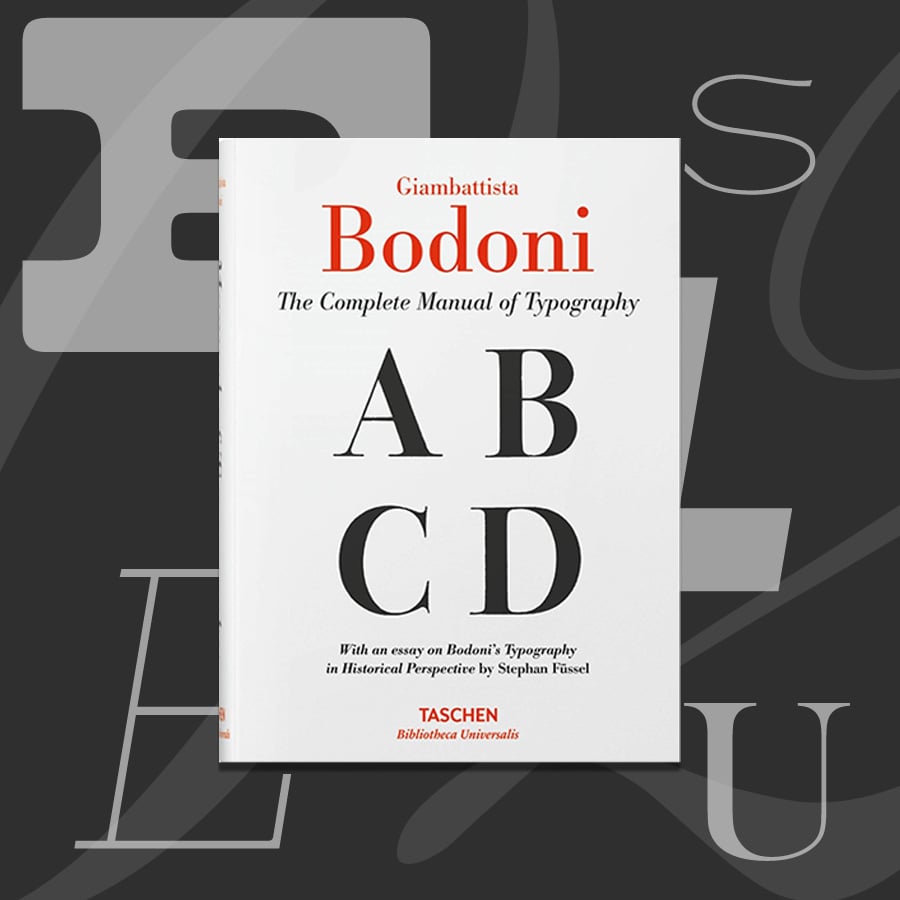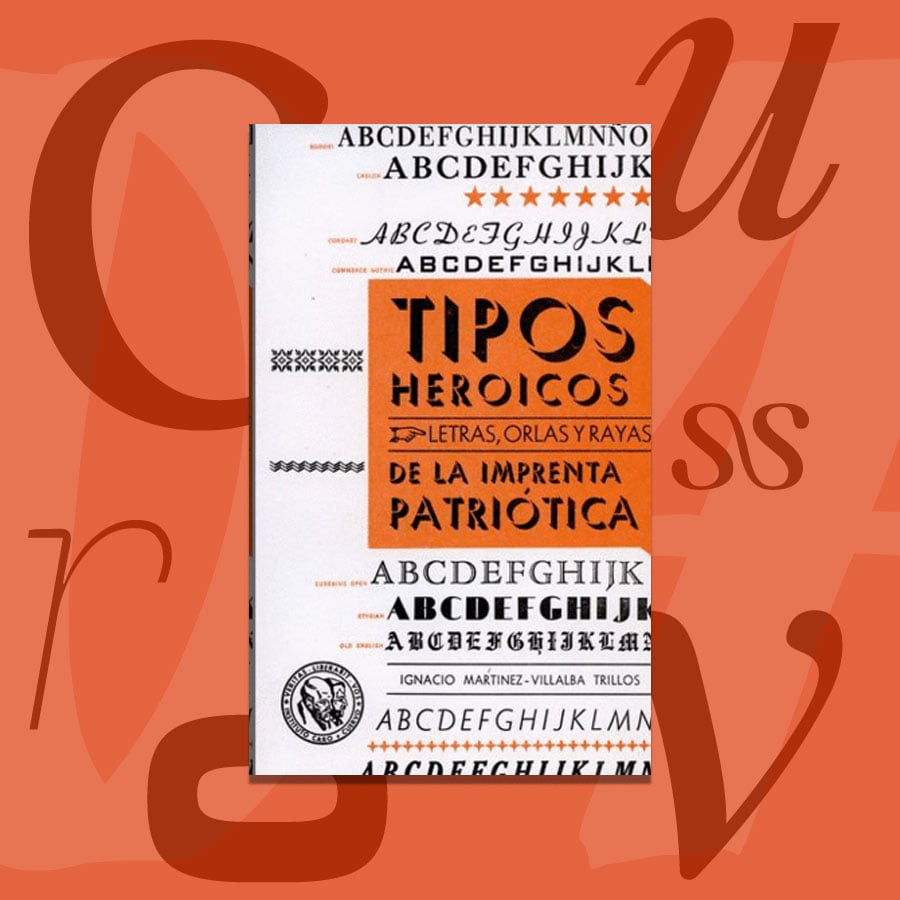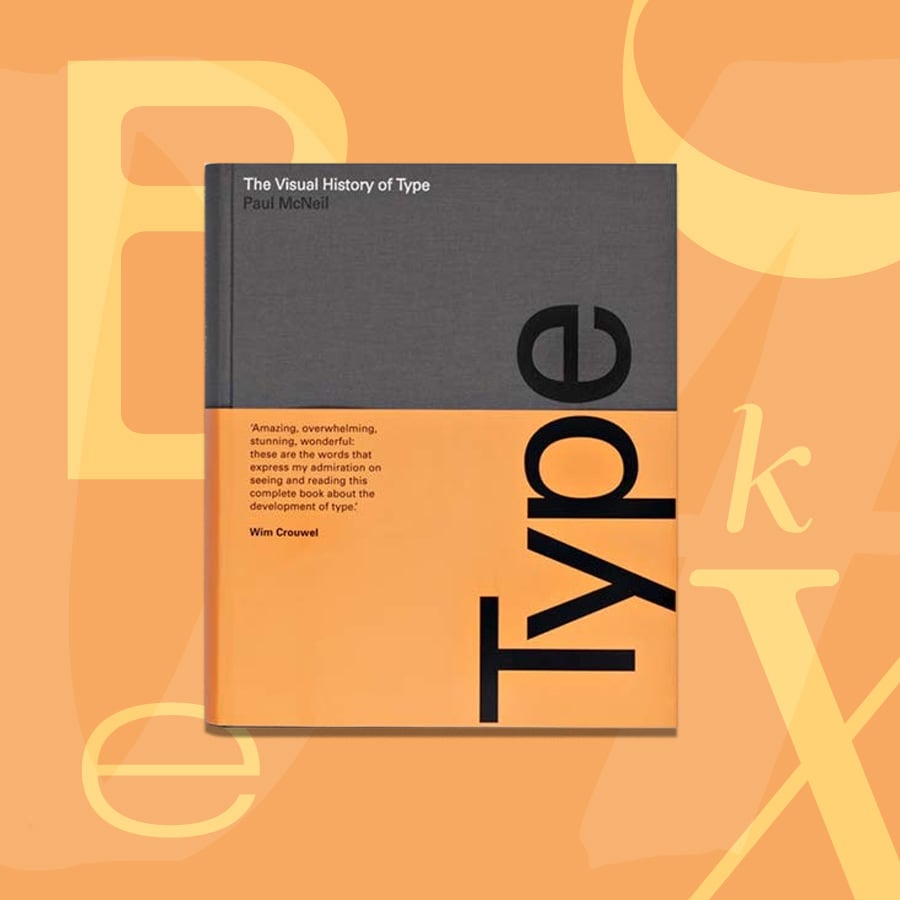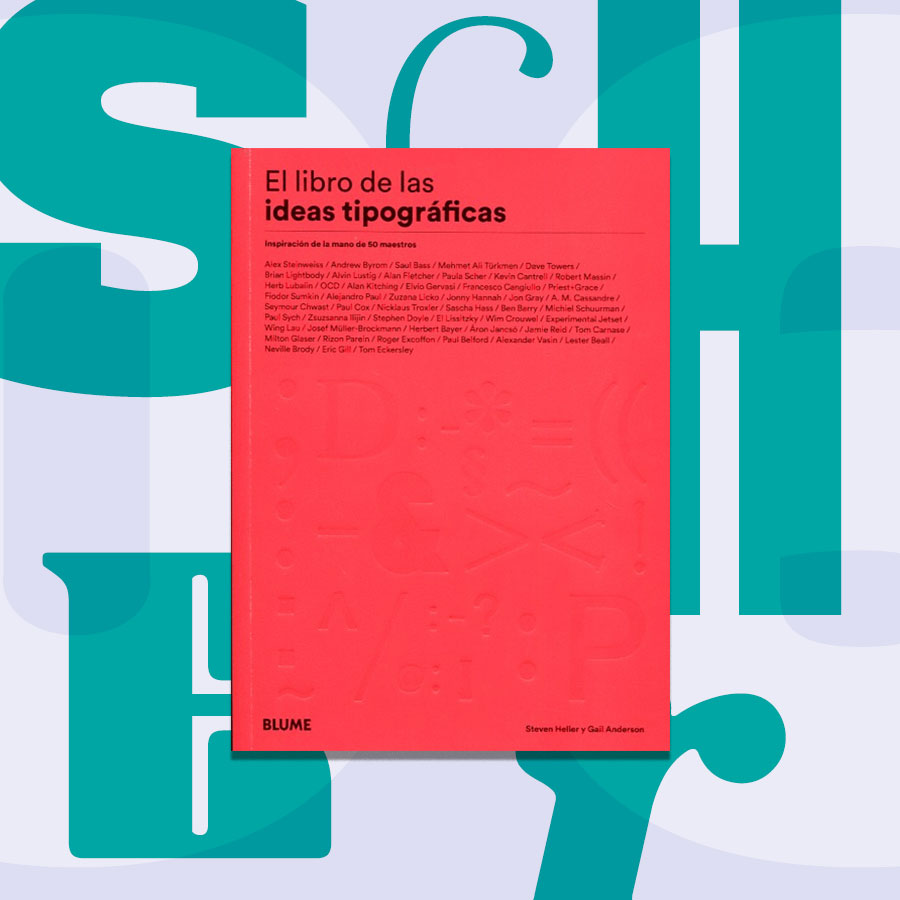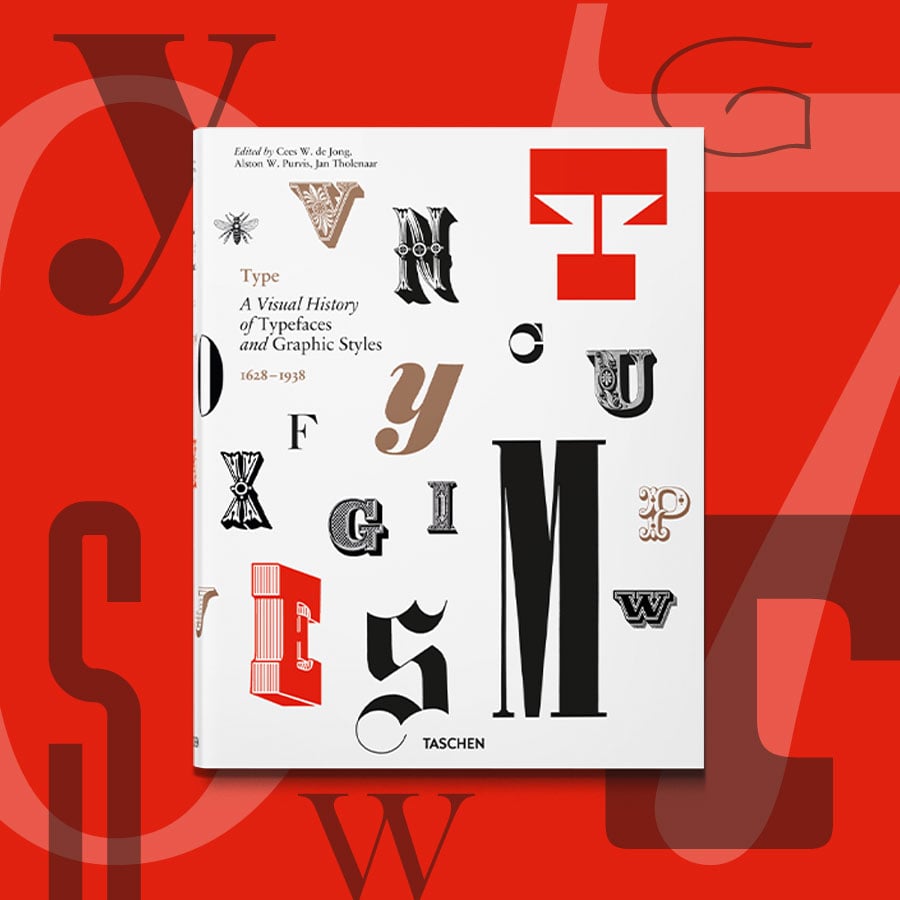
Libros de tipografía indispensables para cualquier diseñador
En esta selección bibliográfica las letras son protagonistas, no como medio sino como fin. Libros que pueden servir como inspiración, como fuentes de información y, sin duda, como piezas de diseño valiosas por sí mismas.
Hay algo de mágico en poder cifrar las ideas y plasmarlas con un sistema de símbolos que otros entienden también. En El infinito en un junco, Irene Vallejo escribió: “me gusta imaginar a nuestros ancestros saboreando la excitación de plasmar por primera vez sus pensamientos; cuando descubrieran que el amor, el odio, el terror, el desaliento y la esperanza podían escribirse”. Las letras –como la voz– nos permitieron transformar el pensamiento en piedra, papiro, papel; sustrato susceptible de ser leído.
Las letras y los símbolos que las complementan, a su vez, con su potencia expresiva, han ido tomando formas distintas e intencionadas de la mano de escribas, artesanos, linotipistas, diseñadores. Está en sus manos que los elementos tipográficos puestos por ahí realmente se lean y cumplan su función comunicativa, pero también tienen que asegurarse de usar un modo o estilo de presentar las letras que corresponda al contexto en el que van a ser leídas. La legibilidad que se requiere en una señalética no hace falta en un fanzine de las Guerrilla Girls.
La labor del tipógrafo es, entonces, la de disponer el catálogo de letras, tipos, orlas, signos y números para que funcionen en lugares específicos e indiquen al lector cómo leer. Esta es una selección bibliográfica para quienes reconocen en las letras su lugar de creación y que buscan siempre referentes y métodos que sirvan para construir nuevas formas de comunicar el mundo.
De un estudio
Specimen Bastarda
Bastarda Design Studio
01 Bastarda Especimen
Un espécimen o specimen es una publicación donde aparece una familia tipográfica y el detalle de cada uno de sus cuerpos. Solía usarse –y algunos lo hacen todavía hoy– para ver cómo era el comportamiento en impreso de las letras y de su conjunto en diferentes tamaños y así decidir si era la ideal para el producto que quería sacarse. Bastarda es un estudio de diseño bogotano fundado por Jason Guzmán Munevar y Sebastián Castellanos de la Hoz y se definen a sí mismos como “una fundidora de tipografía independiente, enfocada en la producción y distribución de fuentes para proyectos de branding”. En el 2020 lanzaron una publicación llamada Specimen Bastarda como un guiño a su historia.
El libro está impreso en rosa pálido y verde oscuro, está redactado en inglés y español y no tiene tapa, sino una encuadernación cosida con hotmelt al descubierto. Adentro está el resumen de los tres primeros años del estudio tanto de proyectos comerciales como desarrollos que hacen internamente. Hay letras, números y caracteres especiales de todos los tamaños posibles acompañados de imágenes de la tipografía en uso, de nubes o de un cantante en escena. Specimen Bastarda es un catálogo, pero también una forma de entender el interior de un estudio que piensa en las letras como un objeto completo de diseño.
De un ícono
The Complete Manual of Typography
Giambattista Bodoni
Taschen
Fue su padre quien le enseñó el oficio de impresor y de tipógrafo a Giambattista Bodoni (1740). El primer trabajo que tuvo en este oficio ancestral fue en la imprenta de la Congregación para la Propagación de la Fe, pero más tarde el Duque de Parma lo nombró director de la Stamperia Reale. El cuidado que ponía en cada letra de los libros, además de la encuadernación y el uso de tintas variadas, hizo que fueran sus ediciones las más pedidas en el mercado aristocrático de la época.
En 1813 Bodoni falleció y póstumamente su esposa, Margherita Dall’Aglio, publicó el Manuale Tipográfico que en la actualidad lo reedita Taschen bajo el nombre The Complete Manual of Typography. En este libro se hacen evidentes los cuatro principios que Bodoni consideraba que hacían una buena topografía: uniformidad de diseño, definición y nitidez, buen gusto y encanto. Esto se nota en las 142 familias de tipografías consignadas allí que se complementan con ornamentos, símbolos y florituras.
De estudio
Pensar con tipos
Ellen Lupton
Editorial GG
224 páginas
2011
La estadounidense Ellen Lupton parece tener más horas en el día que cualquiera. Es escritora, docente, diseñadora y curadora senior en el Cooper Hewitt Smithsonian Design Museum en Nueva York, uno de los museos de diseño más importantes y versátiles del mundo. Entre sus libros ha contado historias sobre la Bauhaus, el feminismo y el diseño gráfico, el storytelling y, por supuesto, la tipografía. Entre los libros que ha dedicado al diseño de letras, Pensar con tipos es uno de los más prácticos y difundidos. “Este no es un libro de fuentes. Es un libro sobre cómo utilizarlas”, dice la portada de la edición en español.
Pensar con tipos empieza proyectando la letra como una entidad independiente pero rápidamente la piensa dentro de un texto e incluso el texto dispuesto en piezas de diseño. Las tipografías son vistas aquí como composiciones útiles y significantes, como elementos capaces de decirlo todo. Este es un libro para cualquiera que trabaje con letras: editores, diseñadores y escritores pueden aprovecharlo de igual manera.